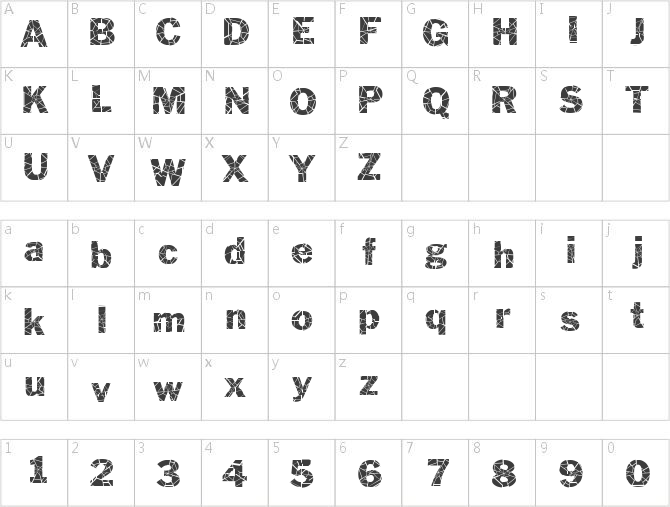
FZ BASIC 56 CRACKED
FZ BASIC 56 CRACKED介紹
FZ BASIC 56 CRACKED字體字庫是一款讓人賞心悅目、百看不厭的英文字體,適合各類廣告和產(chǎn)品包裝設(shè)計應(yīng)用,字體大小0.13MB,格式為ttf字體,上傳用戶是誠澤永信,作者/版權(quán)方為未知